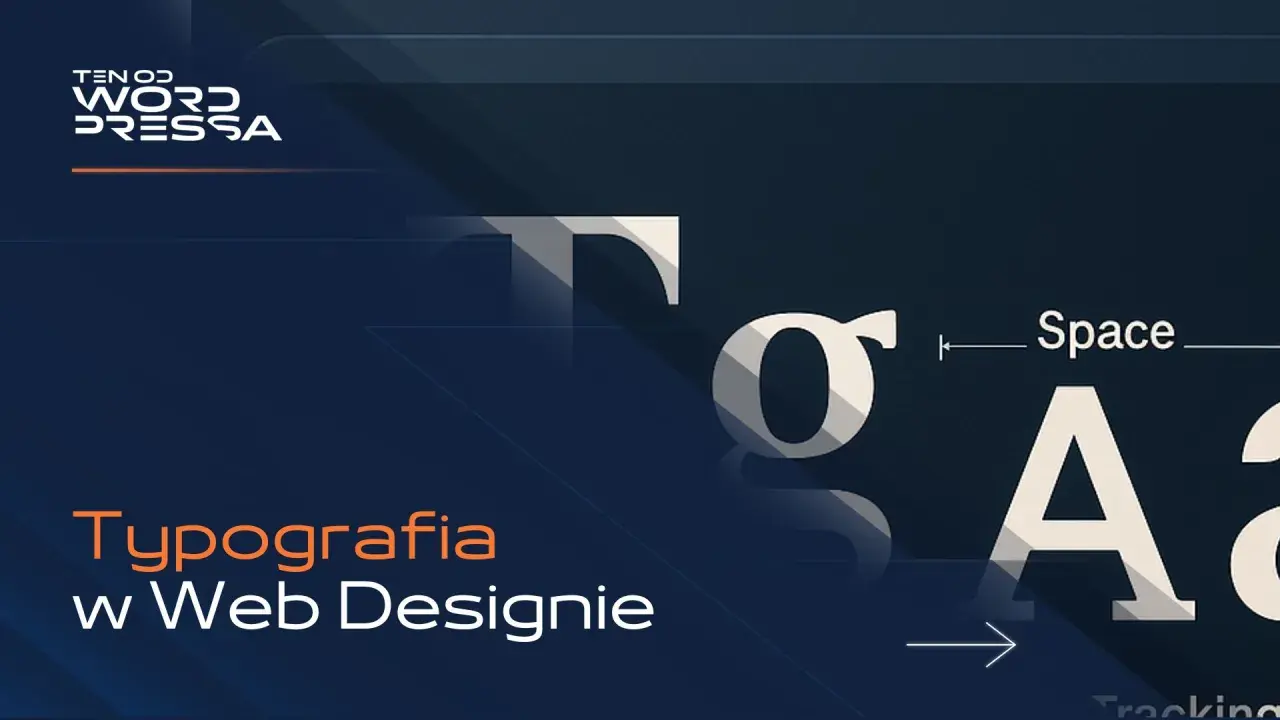
Dobry napis potrafi przyciągnąć wzrok, ale to sposób ułożenia całego tekstu decyduje, czy odbiorca go przeczyta. W tym artykule wyjaśniam, czym jest typografia, czym różni się od liternictwa i kaligrafii oraz jak świadomie dobierać krój, wielkość, odstępy i układ liter w plakacie, książce, logo czy projekcie internetowym.
Typografia porządkuje tekst i nadaje mu określony charakter
- Typografia obejmuje wybór kroju pisma, jego rozmiaru, koloru, odstępów i rozmieszczenia tekstu.
- Liternictwo polega na projektowaniu lub rysowaniu pojedynczych liter i napisów, często specjalnie dla jednego projektu.
- Krój pisma to wizualny projekt znaków, a font jest jego cyfrowym zapisem używanym w programie.
- Czytelność zależy między innymi od interlinii, długości wiersza, kontrastu i właściwego porządku nagłówków.
- Dobry skład nie konkuruje z treścią. Pomaga odbiorcy szybko zrozumieć komunikat.
Typografia to nie tylko wybór ładnego fontu
Najprościej mówiąc, typografia zajmuje się graficzną formą tekstu i relacjami między znakami. Obejmuje zarówno dobór kroju pisma, jak i wielkość liter, grubość, kolor, odstępy, wyrównanie oraz układ tekstu na stronie lub ekranie.
Jej zadaniem jest połączenie dwóch rzeczy, które czasem trudno pogodzić: czytelności i charakteru. Tekst ma być łatwy do odczytania, ale jednocześnie powinien pasować do tematu. Inaczej zaprojektujemy zaproszenie na wystawę malarstwa, inaczej instrukcję obsługi, a jeszcze inaczej okładkę albumu muzycznego.
W praktyce typografia działa jak niewidoczny przewodnik. Podpowiada, co przeczytać najpierw, gdzie kończy się jedna myśl i które informacje są najważniejsze. Nawet bardzo dobry tekst może wypaść słabo, jeśli został złożony zbyt małą czcionką, ma za ciasne odstępy albo używa kilku przypadkowych krojów naraz.
Krój pisma, font i czcionka
Te trzy określenia bywają stosowane zamiennie, choć technicznie nie oznaczają dokładnie tego samego. Krój pisma to projekt i charakter całego zestawu znaków, na przykład szeryfowych, bezszeryfowych lub odręcznych. Font jest cyfrowym plikiem, który pozwala użyć danego kroju w komputerze.
Czcionka w tradycyjnym drukarstwie oznaczała fizyczny nośnik pojedynczego znaku, najczęściej metalowy element używany w druku wypukłym. W codziennym języku słowo „czcionka” często oznacza jednak font. Nie jest to duży problem w zwykłej rozmowie, ale przy pracy projektowej precyzyjniejsze określenie pomaga uniknąć nieporozumień.
Co typografia zmienia w odbiorze
Ten sam komunikat zapisany krojem o delikatnych szeryfach może wyglądać spokojnie i elegancko, a po zastosowaniu ciężkiego fontu blokowego stanie się mocny, reklamowy i bardziej bezpośredni. To nie magia, tylko efekt skojarzeń kulturowych, proporcji liter oraz kontekstu, w którym je widzimy.
Nie traktuję jednak psychologii fontów jak zbioru sztywnych reguł. Najważniejszy jest cały układ, a nie pojedyncza nazwa kroju. Nawet klasyczny krój może wyglądać nowocześnie, jeśli zestawi się go z dużą ilością światła, prostą kompozycją i ograniczoną paletą kolorów.
Typografia a liternictwo i kaligrafia
Liternictwo i typografia są blisko siebie, ale opisują różne działania. Liternictwo skupia się na tworzeniu liter, natomiast typografia częściej dotyczy ich wyboru, organizowania i stosowania w większej kompozycji.
| Dziedzina | Na czym polega | Przykład zastosowania |
|---|---|---|
| Typografia | Dobór i układ gotowych znaków oraz tekstów | Skład książki, strona internetowa, plakat informacyjny |
| Liternictwo | Rysowanie, konstruowanie lub projektowanie liter i napisów | Logo, mural, ręcznie wykonany szyld, tytuł plakatu |
| Kaligrafia | Piękne i świadome pisanie przy użyciu określonego narzędzia | Zaproszenia, dyplomy, ręczne inskrypcje |
Przykładowo, napis „Kino letnie” namalowany pędzlem specjalnie na jeden plakat będzie przede wszystkim realizacją literniczą. Jeśli ten sam napis zostanie złożony z cyfrowego fontu i ustawiony razem z opisem wydarzenia, godziną oraz miejscem, wchodzimy w obszar typografii.
Granice nie zawsze są ostre. Liternik może korzystać z zasad typograficznych, a typograf może modyfikować gotowe litery. Właśnie dlatego ręcznie zaprojektowany nagłówek i zwykły tekst pomocniczy często dobrze współpracują. Indywidualność pojawia się w literach, a porządek w ich układzie.
Z jakich elementów składa się dobry skład tekstu
Typografia nie kończy się na wybraniu kroju. O jakości projektu decydują drobne ustawienia, które na pierwszy rzut oka mogą wydawać się nieważne. To one często przesądzają o tym, czy tekst wygląda profesjonalnie.
| Element | Znaczenie | Praktyczna wskazówka |
|---|---|---|
| Stopień pisma | Wielkość tekstu | Dla dłuższego tekstu na ekranie dobrym punktem wyjścia jest około 16 px. |
| Interlinia | Odstęp między wierszami | Przy tekście ciągłym często sprawdza się wartość 1,4-1,6 wysokości pisma. |
| Kerning | Korekta odstępu między konkretnymi parami liter | Ma szczególne znaczenie w dużych nagłówkach i logotypach. |
| Tracking | Ogólne rozstrzelenie lub zagęszczenie całego tekstu | Delikatne zwiększenie odstępów może pomóc w krótkich wersalikach. |
| Wyrównanie | Sposób ustawienia tekstu względem kolumny | Do długiego tekstu najczęściej wybieram wyrównanie do lewej. |
Hierarchia pomaga czytać szybciej
Dobrze zaprojektowany tekst ma wyraźną hierarchię. Nagłówek powinien być większy lub mocniejszy od akapitu, śródtytuł powinien oddzielać kolejne myśli, a podpis pod ilustracją nie może konkurować z główną treścią.
Nie trzeba budować hierarchii wyłącznie za pomocą dużych rozmiarów. Pomagają także grubość kroju, kolor, odstępy i miejsce na stronie. Zwykle wystarczą dwa kroje pisma albo jeden krój w kilku odmianach. Większa liczba fontów szybko tworzy wizualny bałagan.
Przeczytaj również: Jak ćwiczyć literę A? Kaligrafia i brush lettering
Czytelność wymaga przestrzeni
Jednym z częstszych błędów jest upychanie tekstu tak, aby zmieścić jak najwięcej informacji. Tymczasem pusta przestrzeń, czyli światło, oddziela bloki treści i pozwala odpocząć wzrokowi. Przy tekście internetowym dobrze sprawdza się długość wiersza wynosząca mniej więcej 45-75 znaków.
Interlinia również nie powinna być przypadkowa. Zbyt mała sprawia, że wiersze zlewają się ze sobą, a zbyt duża rozbija akapit. W projekcie artystycznym można świadomie odejść od tych zasad, ale trzeba wiedzieć, że wtedy czytelność ustępuje miejsca ekspresji.
Jak dobrać typografię do konkretnego projektu
Dobór kroju zaczynam od pytania, co odbiorca ma poczuć i zrobić, a dopiero później oglądam katalog fontów. Typografia dla galerii sztuki może być eksperymentalna, ale opis godzin otwarcia nadal powinien dać się odczytać bez wysiłku.
- Określ funkcję tekstu. Innego kroju potrzebuje długi artykuł, innego tytuł plakatu, a jeszcze innego krótkie oznaczenie na opakowaniu.
- Wybierz jeden główny charakter. Zdecyduj, czy projekt ma być spokojny, elegancki, techniczny, zabawny, surowy czy dekoracyjny.
- Sprawdź polskie znaki. Font powinien poprawnie zawierać ą, ć, ę, ł, ń, ó, ś, ż i ź. Brak któregoś znaku dyskwalifikuje go w polskim tekście.
- Zbuduj hierarchię. Ustal rozmiary nagłówków, tekstu podstawowego, podpisów i wyróżnień, zanim zaczniesz dopieszczać szczegóły.
- Przetestuj projekt w docelowej skali. Font, który dobrze wygląda na powiększonym ekranie, może być nieczytelny na telefonie albo w małym druku.
Do książki lub dłuższego artykułu zwykle wybieram krój o spokojnych proporcjach i wyraźnych różnicach między znakami. Na plakacie można pozwolić sobie na większą ekspresję, bo tekst jest krótki i ogląda się go z większej odległości. Im więcej tekstu, tym mniej miejsca na dekoracyjne komplikacje.
W przypadku logo liternictwo często daje lepszy efekt niż gotowy font użyty bez zmian. Nawet mała korekta kształtu jednej litery może sprawić, że znak stanie się rozpoznawalny. Trzeba jednak pamiętać o licencji. Nie każdy font dostępny w internecie można legalnie wykorzystać w identyfikacji marki lub w produkcie przeznaczonym do sprzedaży.
Błędy, przez które typografia traci siłę
Początkujący projektanci często skupiają się na samej nazwie fontu, a pomijają proporcje i układ. Tymczasem nawet popularny krój będzie wyglądał źle, jeśli tekst zostanie niewłaściwie ustawiony.
- Zbyt wiele krojów pisma osłabia hierarchię. Jeśli każdy fragment wygląda inaczej, odbiorca nie wie, co jest najważniejsze.
- Rozciąganie liter w programie graficznym niszczy ich proporcje. Lepiej użyć właściwej odmiany fontu, na przykład condensed albo semi-bold.
- Wersaliki w długich akapitach spowalniają czytanie, ponieważ wszystkie słowa mają podobny prostokątny kształt.
- Zbyt mały kontrast między tekstem a tłem może wyglądać subtelnie, ale pogarsza dostępność i czytelność.
- Automatyczne justowanie potrafi tworzyć nieestetyczne przerwy między słowami, zwłaszcza w wąskich kolumnach.
- Brak polskich znaków zmusza do zastępowania fontu innym krojem albo prowadzi do przypadkowych różnic w wyglądzie liter.
Nie każda zasada musi być stosowana sztywno. Plakat artystyczny może celowo mieć nierówne odstępy, a literniczy napis może łamać reguły klasycznego składu. Różnica polega na tym, czy decyzja jest świadomym zabiegiem, czy wynika z braku kontroli nad projektem.
Najbardziej przecenianym rozwiązaniem jest moim zdaniem szukanie „idealnego” fontu. Znacznie większą różnicę robi dopracowanie relacji między literami, odpowiedni kontrast i konsekwentny układ. Dobry krój nie uratuje chaotycznej kompozycji.
Litera ma przyciągać wzrok, ale tekst powinien prowadzić dalej
Typografia łączy stronę użytkową i artystyczną. Może budować nastrój, wzmacniać markę i podkreślać charakter plakatu, ale jej podstawowym zadaniem pozostaje sprawne przekazywanie treści.
Gdy rozróżnimy typografię od liternictwa i kaligrafii, łatwiej zdecydować, czy potrzebujemy gotowego fontu, ręcznie zaprojektowanego napisu, czy po prostu lepszego składu. Warto zacząć od prostego układu, sprawdzić go w rzeczywistym rozmiarze i dopiero później dodawać dekoracyjne rozwiązania.
Najlepszy projekt nie zawsze zwraca uwagę od razu. Czasem jego sukces polega na tym, że odbiorca bez przeszkód czyta, rozumie i zapamiętuje komunikat, nawet nie zastanawiając się, dlaczego wszystko wygląda tak naturalnie.